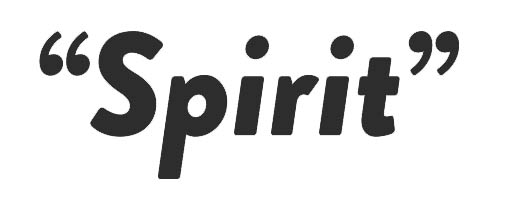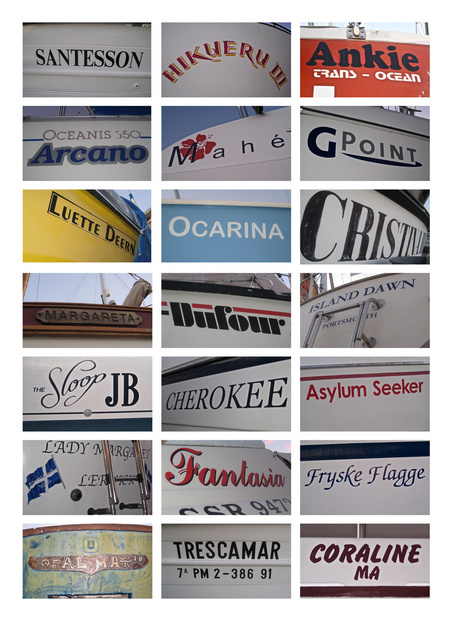
Namenszug für eine Segelyacht ;)
zu der qualität der digitalisierungen kann ich nichts sagen, ich hab außer jener website noch keine schrift in aktion gesehen
Die Digitalisierungen sind wesentlich besser, als man es nach Anblick der Internetseiten annehmen würde.
Ich bin gerade nach Hause gekommen und habe Eure vielen Vorschläge entdeckt, toll, ich freue mich! Ich schaue da gleich mal in Ruhe durch. Nur so viel schon mal vorab: Ein Problem weniger habe ich – der Name des Bootes wird nämlich geändert, jippie! Der neue Name steht noch nicht fest, aber ich werde bei der Auswahl ein Auge drauf haben, dass man ihn schöner setzen kann.
Wo an den Bug soll der Schriftzug denn hin? Steuerbord, Backbord, auf beiden Seiten? Ganz nah am Bug oder weiter weg? Wie groß soll der Schriftzug werden? So groß wie auf dem Bild im Wasser oder größer?
Hallo Thorsten, der Schriftzug soll beidseitig auf den Bug gesetzt werden. Gerne etwas größer als bisher, ähnliche Position wie auf dem Wasserbild. :-)
So neutral? Ich könnte mir sowas , vielleicht in Versalien, vorstellen.
Die ist echt nett! Da sollte man einen Bootsnamen wählen, bei dem so eine schöne Ligatur eingesetzt werden kann. ;-)
Lach, mit Eurer tatkräftigen Unterstützung auf alle Fälle! ;-)
Was da so in den Häfen rumdümpelt – unglaublich! Nun stammen die von mir gezeigten Schriftzüge alle von älteren Booten, die gerade in der Werft stehen. Die neuen Boote – insbesondere auch die dicken Motorboote – haben eigentlich noch schlimmere Sachen: verzerrte Schrift, mit Schatten unterlegt, in Gold, von den Schriften ganz zu schweigen … Ich sammle da gerne demnächst mal ein paar Beispiele ein.
Sobald der neue Name steht, werde ich die verschiedenen Schriftvorschläge ausprobieren und dann hier zeigen.
Also ich liebe die Reporter ja sehr, aber auf dem Boot hätte ich dann weder die Modernität, noch die klassische Eleganz unterstrichen.
Ich mag Typografskis Entwurf gerne, der Pferdefuss bei der Sache ist nur, dass die Textbestandteile (Name, Heimathafen, Kennziffer) bei dieser Yacht nicht zusammenstehen werden. Und ohne die Gotham fehlt der Bello dann einfach was. Die Kombi macht in dem Fall ganz viel aus, finde ich.
Der neue Name steht, das Boot wird »Spirit« heißen. :-)
Die hier ist dann aber trotzdem nicht die Richtige, auch wenn’s etwas besser ist als mit »Petra« … :cry:
;-) Einen Hauch eleganter dürfte sie sein … Wie sieht denn Deine Schrift in Versalien aus?
Meines Erachtens noch »schlimmer«. Kapitälchen könnten gehen.
Aber suche lieber was, was von vornherein besser paßt! ;-)